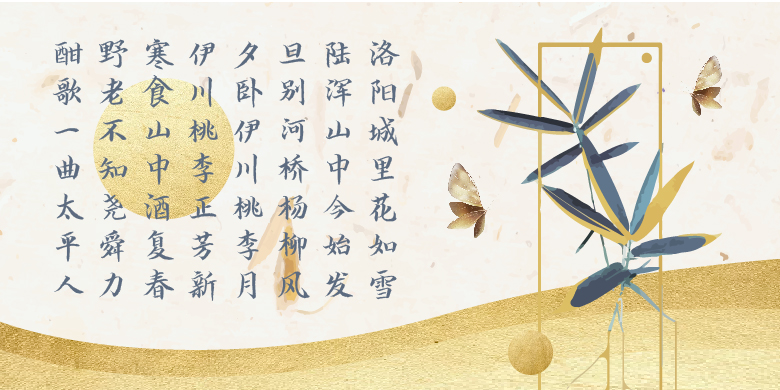
方正字迹-思道小楷
字体品牌: 方正字迹 设计师:易礼然,郑晓清 字体分类:楷书 字体属性:精品字 字符集:大陆简体(GB2312-80) 发布时间: 2021
该字体创作灵感深受清末最后一名状元刘春霖的试卷启发,设计了这款笔画细腻,静中有动,断中有连,结体宽绰秀美的小楷。特别是不同形态的点画,柔美曲折,婀娜多姿,如同美女翩翩起舞,又如新莺千啭百啼。
作者易礼然,字体设计师、国际文字设计协会会员,国家艺术基金班结业。作品多次入选国际大展并被主流报道和杂志刊载,2021年10余作品被意大利GMA博物馆收藏。
作者郑晓清,美术教师,在中国科举博物馆的浸润下自幼就喜欢书法,多次在教师大赛中获奖。